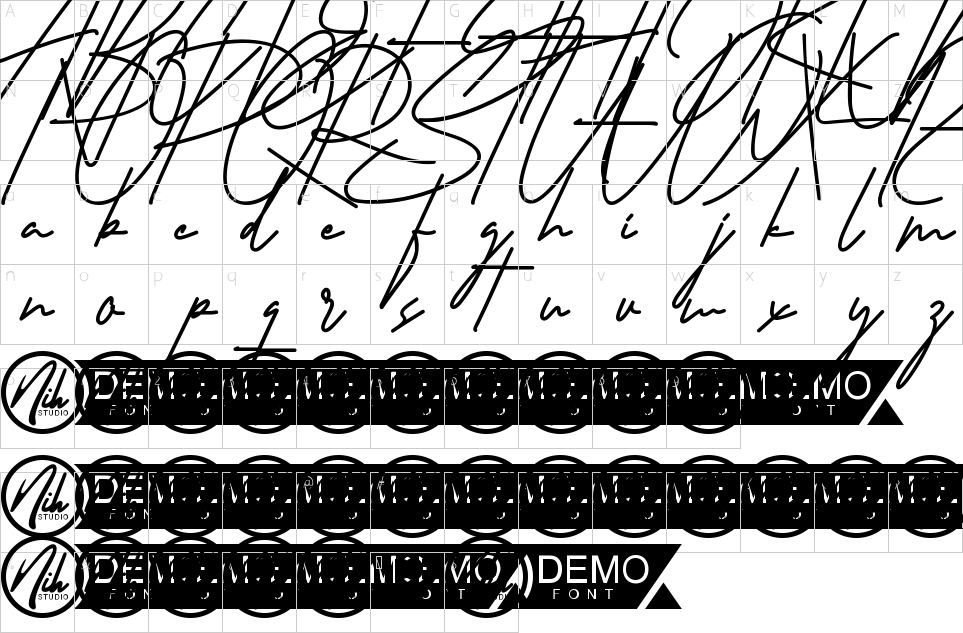
A fonte Amelyn é uma escolha perfeita para designers gráficos em busca de uma opção limpa e elegante. Desenhada por nihstudio, essa fonte gratuita é perfeita tanto para Windows quanto para Mac, tornando-a uma excelente opção para projetos de todos os tamanhos, desde pequenos cartões de agradecimento até maiores projetos de design gráfico. Com seu design minimalista, Amelyn combina facilmente com diversos estilos de design, permitindo que designers criem uma ampla variedade de opções visuais. Descarregada por mais de 3.000 vezes, a Amelyn é uma opção confiável para quem busca qualidade sem comprometer os limites orquestrais. Com ela, você pode alcançar um resultado limpo e elegante em qualquer projeto de design que tenha em mente.